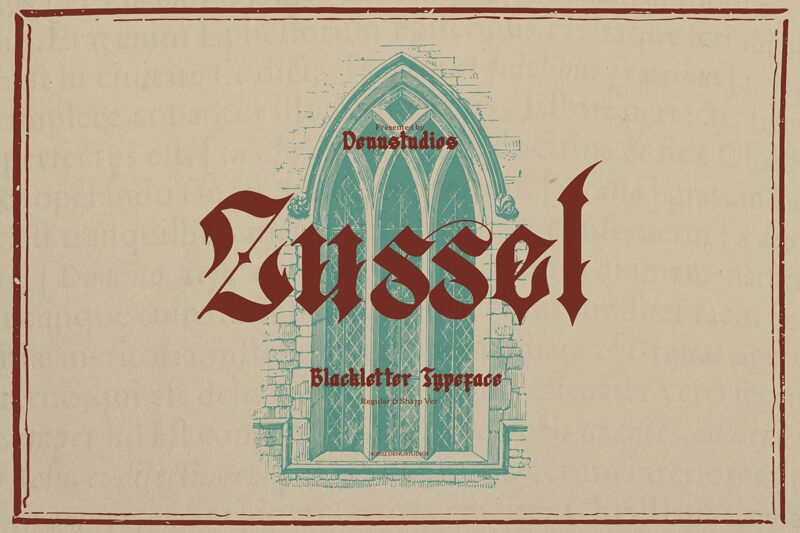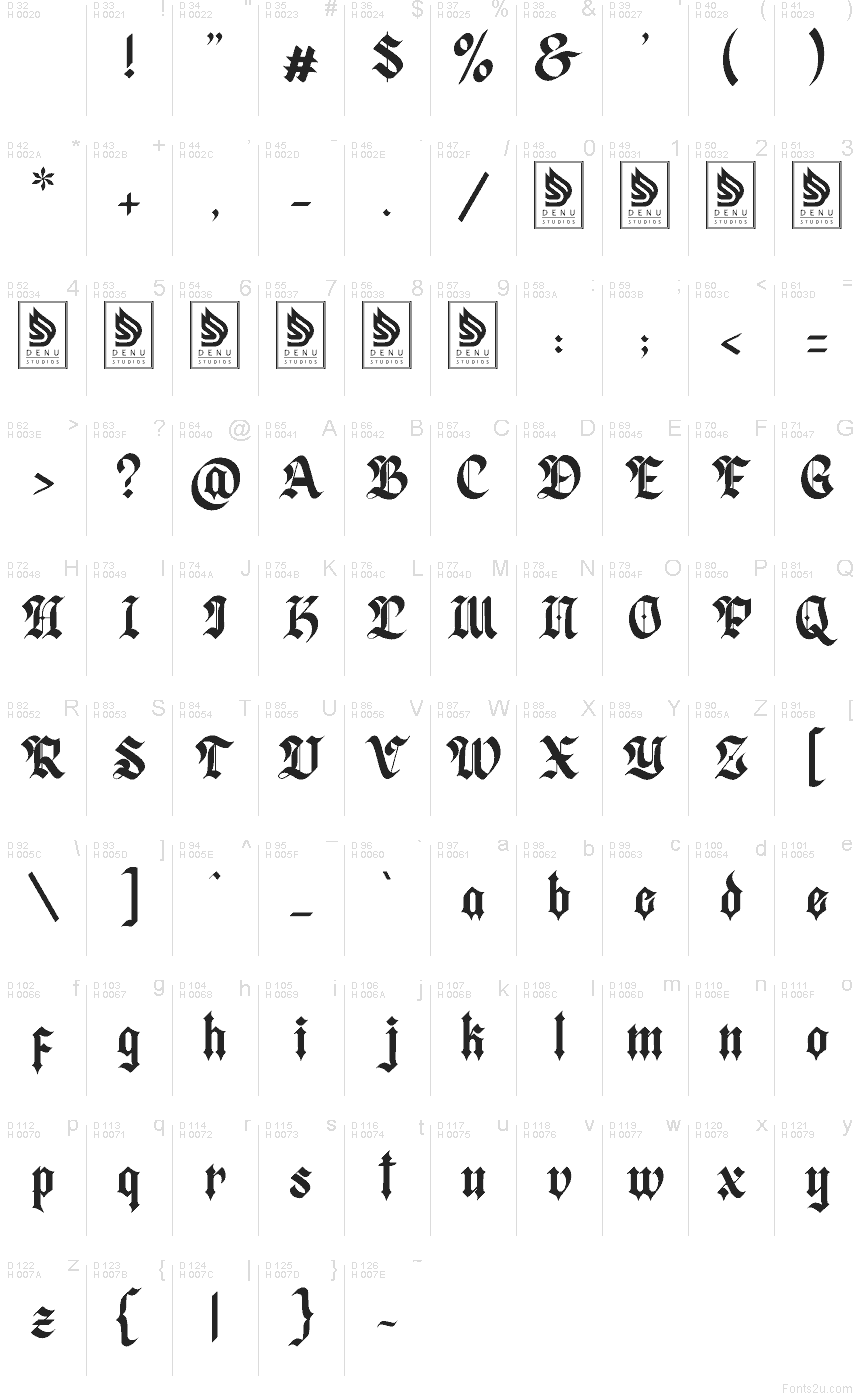
Zussel, créé par Denustudios, est une police gothique médiévale gratuite, caractérisée par des angles noirs tranchants et un dynamisme inspiré du vieux monde. Les caractères allient un rythme vertical soutenu à des courbes généreuses et des angles vifs, conférant à l'ensemble une texture cérémonieuse plutôt que sévère.
Elle est parfaite pour des titres d'affiches, des couvertures de livres fantastiques, des logos de groupes, une identité visuelle pour taverne ou des visuels d'événements qui nécessitent une typographie historique sans tomber dans l'aspect poussiéreux. Grâce à ses formes grasses, compactes et aux jointures ciselées, Zussel fonctionne également très bien pour les titres courts, les cartons de présentation et les initiales de type monogramme, où cette âme manuscrite peut porter la mise en page à elle seule.